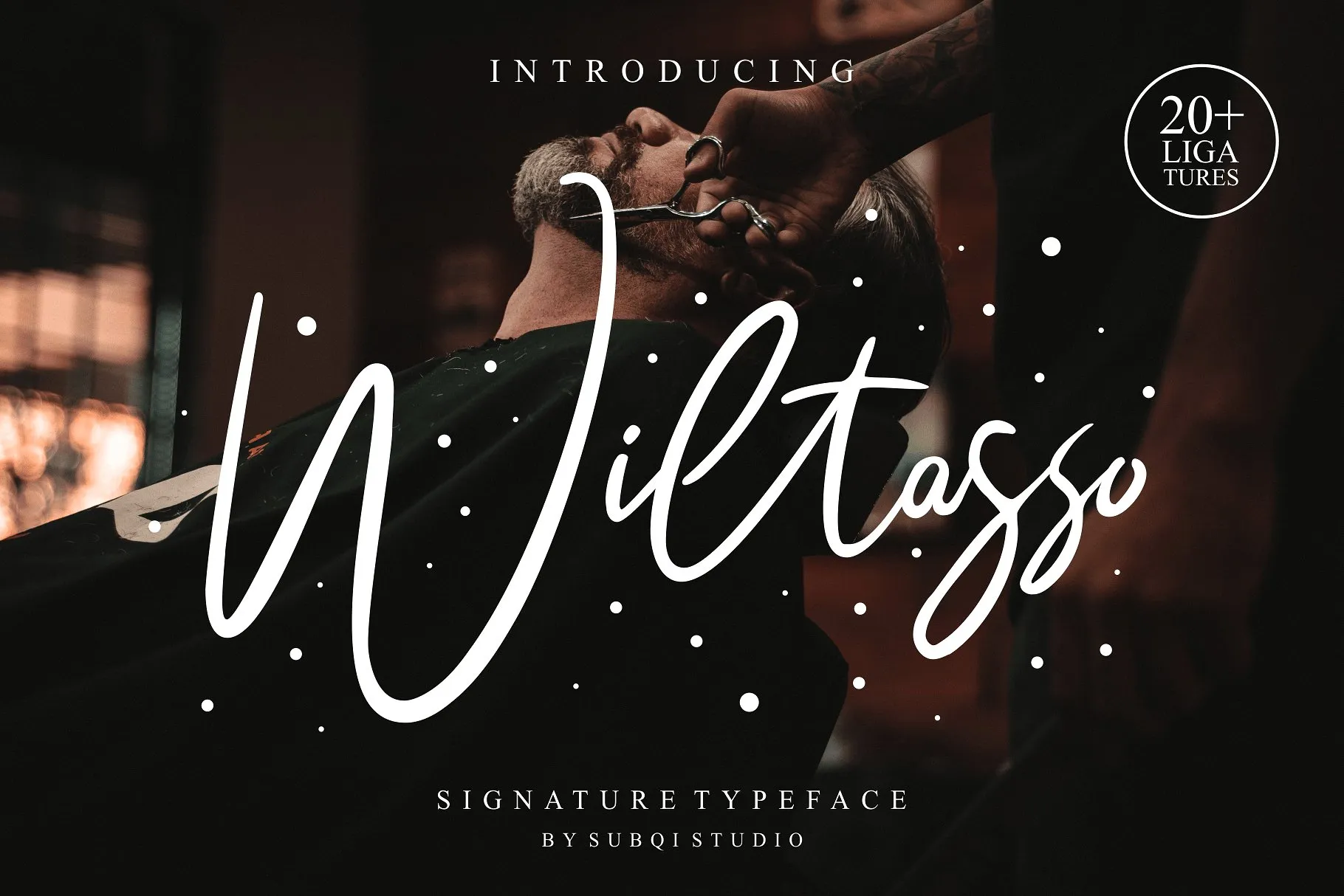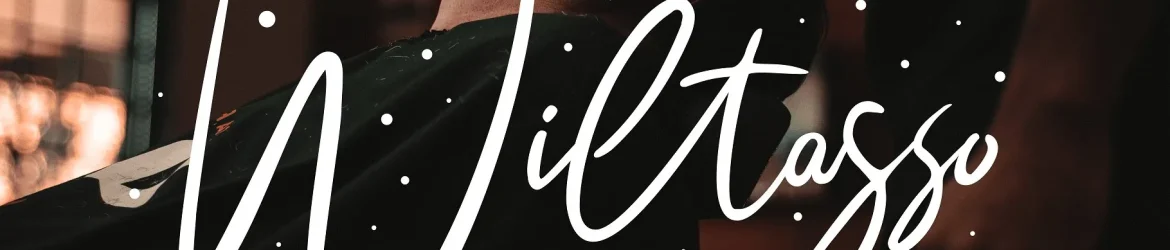
Wiltasso Signature Font – Download Grátis
A Wiltasso é uma nova assinatura moderna para seu portfólio de fontes. Este tipo de letra foi criado a partir de digitais de unha, meticulosamente retratadas para oferecer um toque único e autêntico. Com o desenho minucioso das formas que caracterizam as assinaturas pessoais, esta fonte se destaca perfeitamente para uso em cartões de convite, anúncios, festas, posters, símbolos de marcação, logotipos e até mesmo etiquetas de agenda. A Wiltasso é a escolha ideal para estilos criativos que valorizam personalidade única e design sofisticado. Adicione-a agora à sua coleção de fontes e surpreenda-se com a diversidade de ideias incríveis possíveis.